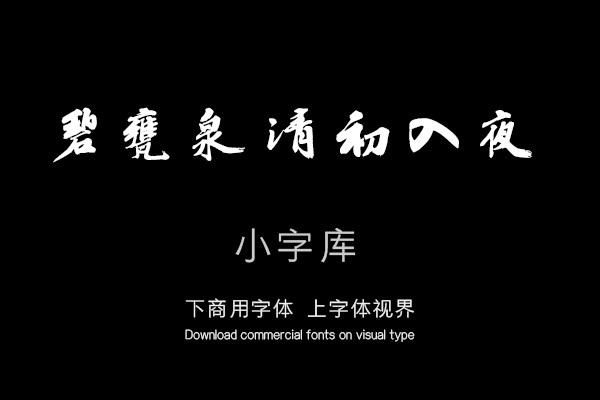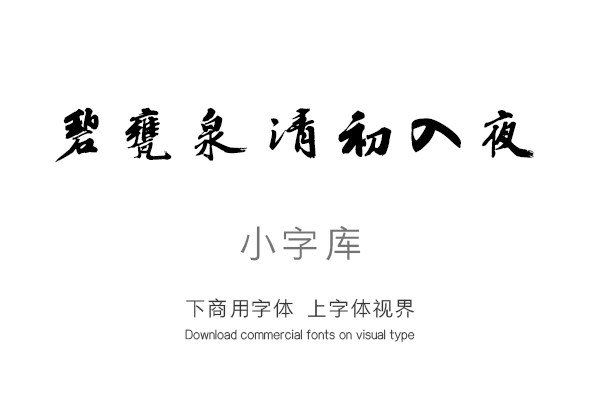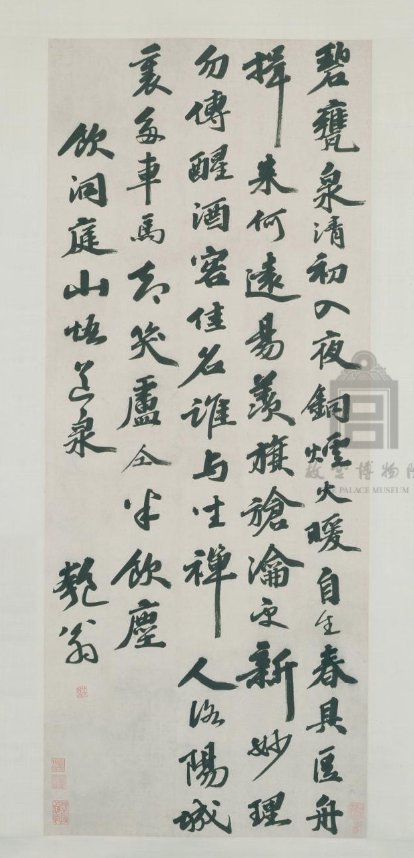
《汉标吴宽饮洞庭山悟道泉诗》是一款根据明代吴宽经典书法作品《饮洞庭山悟道泉诗》,经过再次调整制作的小字库,该小字库共收录了该真迹作品中约74个字体。单字授权
碧瓮泉清初入夜,铜炉火暖自生春。具区舟楫来何远,昜羡旗枪瀹更新。妙理勿传醒酒客,佳名谁与坐禅人。洛阳城里多车马,却笑卢仝半饮尘。饮洞庭山悟道泉。匏翁